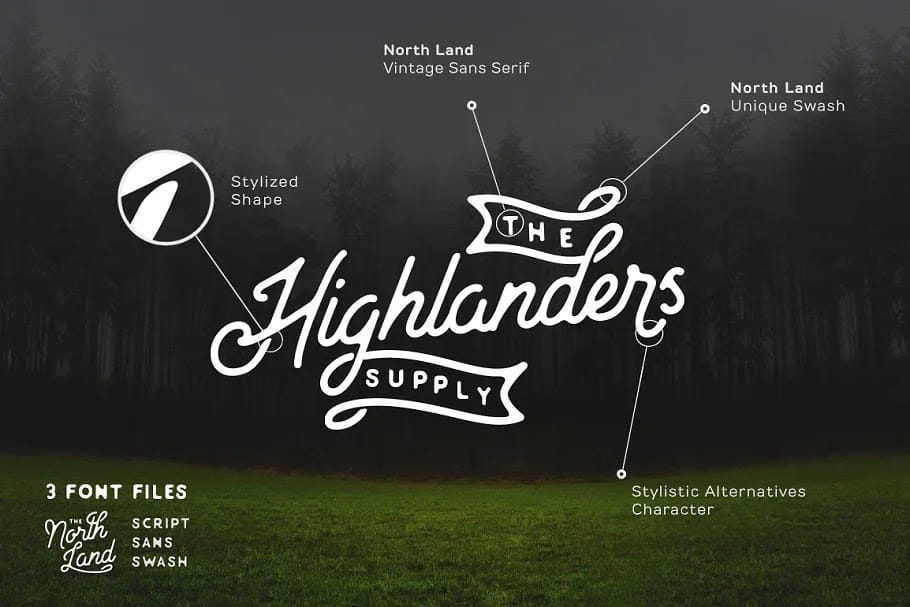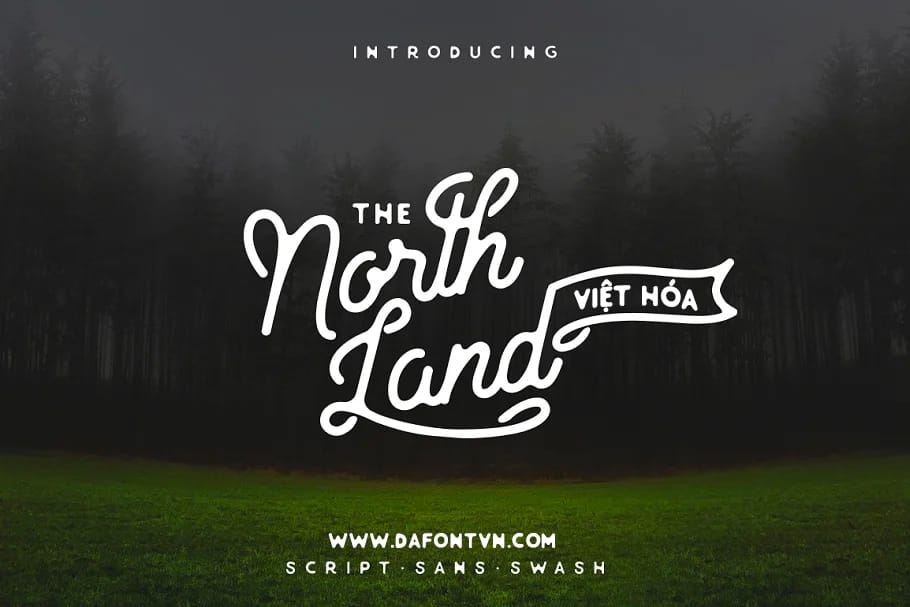
North Land Typeface là một phông chữ cổ điển handlettering lấy cảm hứng từ kiểu
chữ thủ công. Font chữ có các cạnh mịn để mô phỏng cách in cổ điển, vì vậy nó sẽ
mang lại cảm giác cổ điển được vẽ bằng tay.
North Land Việt Hóa đi kèm với 3 kiểu font chữ North Land Script,
North Land Vintage Sans Serif và North Land Swash để được ghép
nối với nhau để có một cái nhìn cổ điển.
Thích hợp cho chữ kỹ thuật số, tài liệu xây dựng thương hiệu, áo thun, bản in,
danh thiếp, báo giá, logo, áp phích, áo thun, chụp ảnh thiên nhiên và có thể
áp dụng cho bất kỳ thiết kế đồ họa nào.